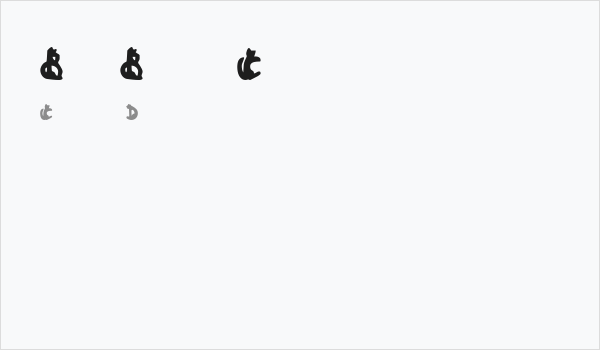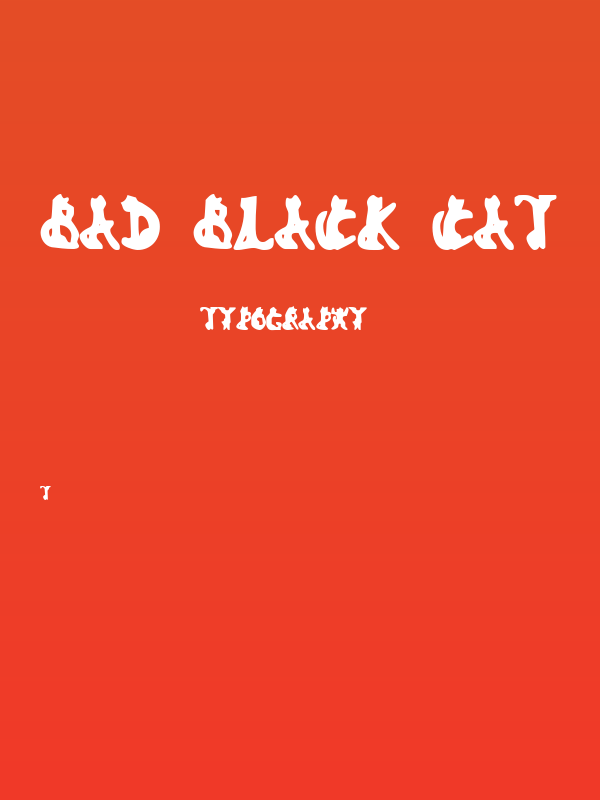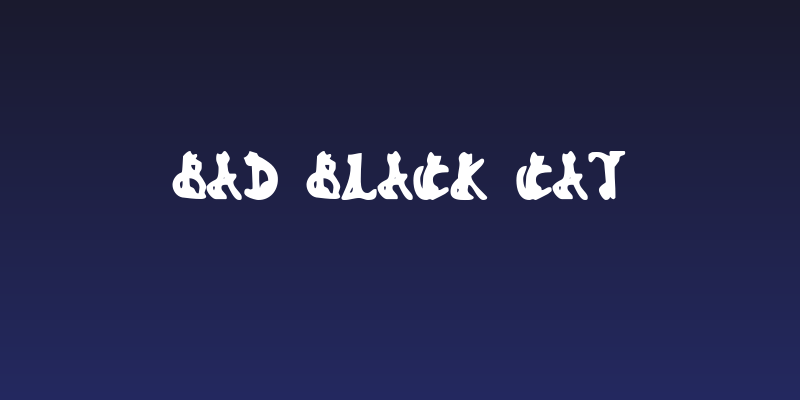
Bad Black Cat Font
| Gesamtstil | Playful, Whimsical, Decorative |
| Vorgeschlagene Projekte | Ideal for children's book covers, playful branding, party invitations, and creative posters. |